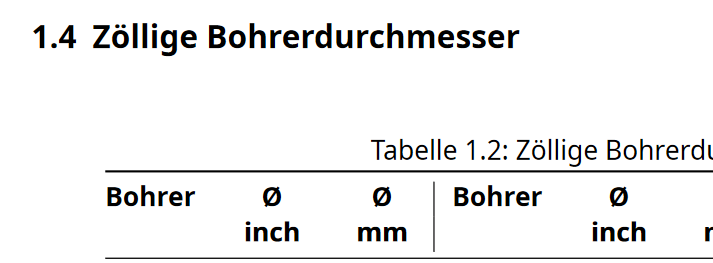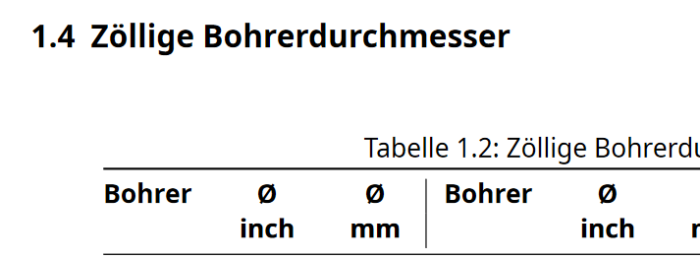
Schriftfamilie für ein Tabellenbuch (Helvetica - FF Meta)
Meine beiden Cent aus Leser-Sicht:
– Minion ist am schlechtesten erfassbar (Schrift zu klein)
– Noto und Source Sans gleich gut lesbar
Source Sans: Hier sind manche Zahlen und Einheiten in einer Serifenschrift, hat das einen tieferen Sinn?
Was bei allen meinem Empfinden nach sehr unelegant ist, sind Trennungen wie Außenge|winde oder Ge|winde. Gibt es in deinem Satzprogramm keine Voreinstellung "ästhetisch" wie beispielsweise in InDesign?
Die Tabellen verwenden fälschlicherweise einen Punkt als Komma.
Noto.
Bei den dichter gesetzten Tabellen würde ich als Leser eine alternierende Zeilenmarkierung in hellem Lichtgrau oder so extrem hilfreich finden.
Und bitte trenne in so losen (1.1) Tabellen händisch. Ich würde mich da nicht auf eine Automatik verlassen wollen, denn KI hin oder her, sinntragende Trennungen mit ästhetischem Anspruch ist doch etwas viel auf einmal.
Oh, und ich hoffe, die Noto hat ein vernünftiges Mal-Zeichen. Das x sieht jedenfalls nach nix aus. Du findest das Mal-Zeichen bei U+00D7.
Zu redundant (Bohrer) für meinen Geschmack: image.thumb.png.50bd74da2cb32f9dadffa1f0a007923c.png
Besser fände ich "Name | ≙ ⌀ in | ≙ ⌀ mm |"
"in" ist doch die Abkürzung für Zoll, oder?
Der Satzspiegel ist merkwürdig. Ich probierte es auf A4 mit dem 9er oder besser dem 12er-Raster. Was dann gut machbar ist, ist, die Tabellen resp. die Spaltenbreiten an die Rasterbreiten anzupassen - das wird augenfällig gut wirken. Und die Zeilen abwechselnd zu unterlegen, wie Phoibos bemerkte, kann auch nicht schaden, eher im Gegenteil.
Der Satzspiegel ist merkwürdig. Ich probierte es auf A4 mit dem 9er oder besser dem 12er-Raster. Was dann gut machbar ist, ist, die Tabellen resp. die Spaltenbreiten an die Rasterbreiten anzupassen - das wird augenfällig gut wirken.
ich weiß nicht, ob ich dich richtig verstanden habe. Du hast eine DIN A4 Seite mit einem 12er Raster erstellt?
Und die Zeilen abwechselnd zu unterlegen, wie Phoibos bemerkte, kann auch nicht schaden, eher im Gegenteil.
Kannst Du mir bitte zeigen, was du genau damit meinst?
Du hast eine DIN A4 Seite mit einem 12er Raster erstellt?
Für ein Layout in A4 ist das Neuner- oder Zwölferraster sehr  nützlich.
Neuner - Zwölfer
Ich habe zwei Beispiele für die  Schriften Noto Sans, Minion und Source Sans Pro erstellt. Ich bin auf eurer Urteil gespannt.
Eine Meinung von einem Nicht-Grafiker. Bin Ingenieur und solche technische Dokumente habe ich fast täglich vor Augen und liebe sie.
Die Minion habe ich gerne als Leseschrift, aber nicht für technische Unterlagen. Geht für mich gar nicht.
Mein eindeutiger Favorit ist die Source Sans. So muss Technisches für mich aussehen. Aber, die "60°" auf Seite 3 sehen furchtbar aus. Die müssten für mich aussehen wie die "60°" auf Seite 3 bei Dokument mit Noto Sans.
Aber, die "60°" auf Seite 3 sehen furchtbar aus.
Da hat LaTeX in den Mathemodus umgeschaltet und die CMR-Schriften anstelle Source Sans benutzt, nehme ich an.